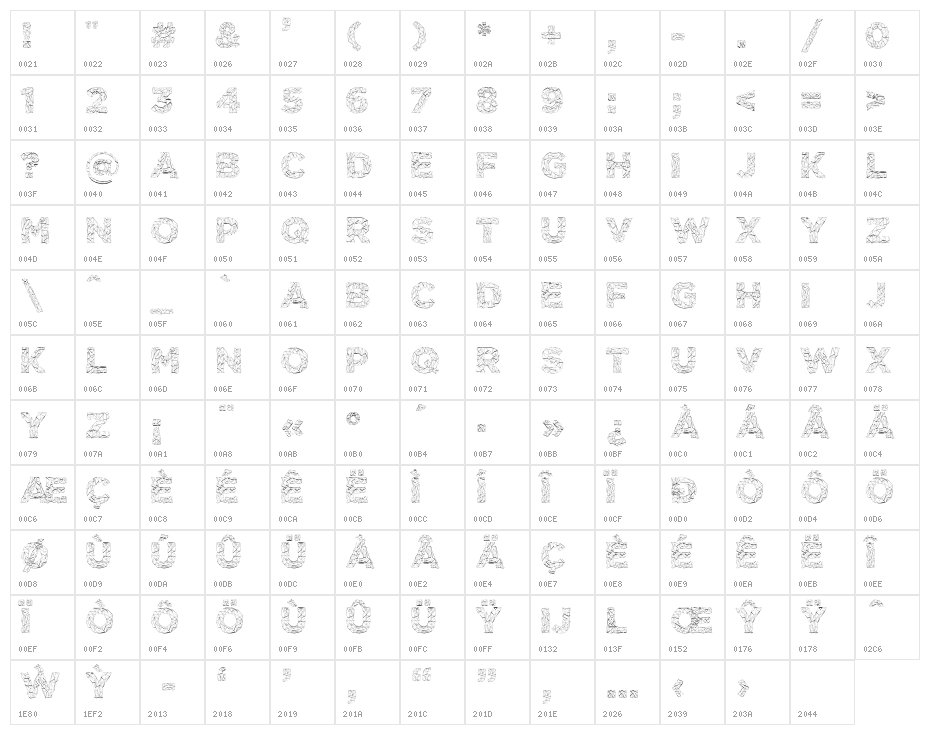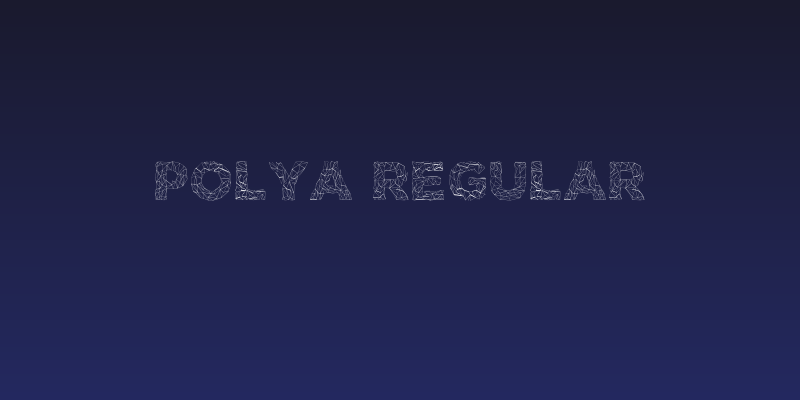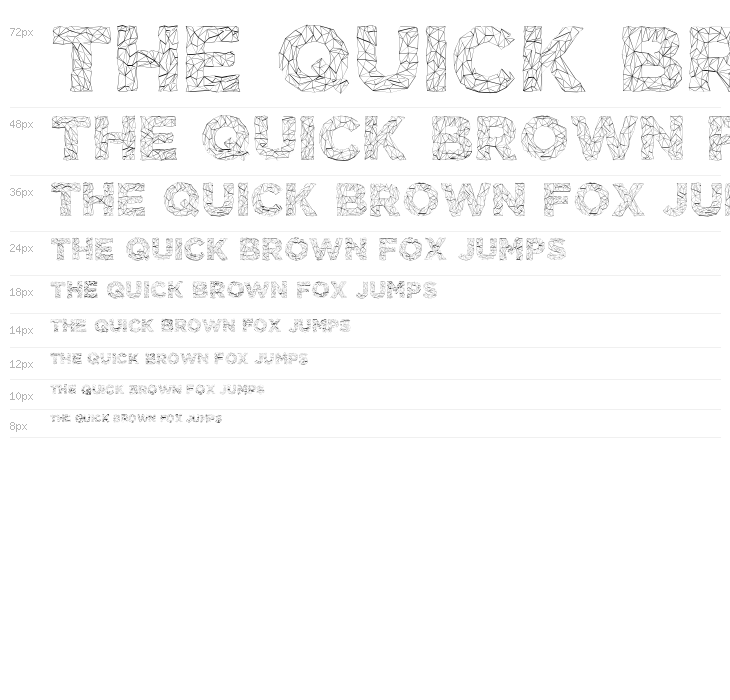
POLYA Regular Font
✎ Thick
| 分类 | Thick |
| 使用场景 | Logos, Headlines, Posters |
| 推荐项目 | Ideal for artistic projects, branding, posters, and digital art where a unique and modern aesthetic is desired. |